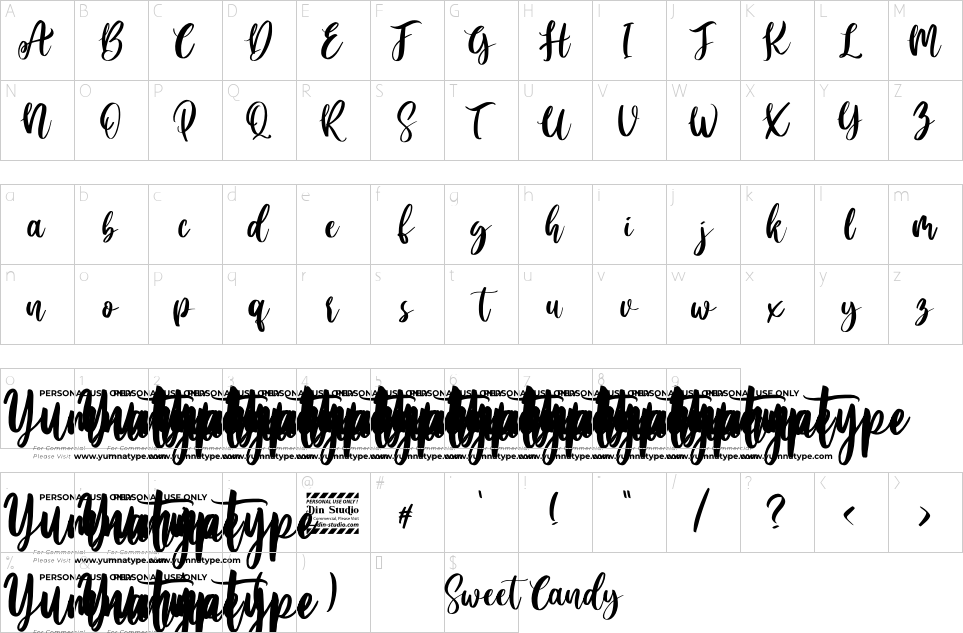
A Sweet Candy Font é uma elegante escolha para os criadores que buscam adicionar um toque de diversão a seus projetos digitais. Desenvolvida pela Yumna Type, esta fonte gráfica tem sido popular entre designers e desenvolvedores web por sua simplicidade e personalidade irresistivelmente suave. Com um design delicado e uma aparência que evoca lembranças de doces caramelo, a Sweet Candy Font é perfeita para dar vida aos seus projetos digitais com um ar descontraído e encantador. Seja você criando cartões personalizados ou desenvolvendo websites amigáveis ao usuário, esta fonte oferece uma solução simples que não compromete o design. Com sua facilidade de uso e baixo download count (aproximadamente 7.152 downloads), a Sweet Candy Font é uma ótima opção para aqueles procurando por um recurso gráfico gratuito e divertido.